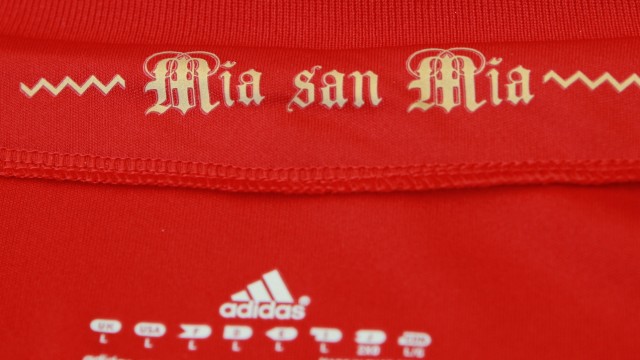
Verzweiflung bei der Suche nach einer Schriftart
ich bin verzweifelt nach der Suche nach einer Schriftart meines eigenen "Vereins".
Es gab leider eine Differenz mit dem ehemaligen Vorsitzenden und der hat das Geheimnis um die Schriftart bis jetzt nicht gelüftet und wird dies auch wohl auch niemals tun.
Deswegen bitte ich Euch mir zu helfen, damit auch in Zukunft nicht alle Plakate, Flyer, Pullis und Briefköpfe eine neue Schriftart benötigen.
Leider habe ich nicht mehr als diese 2 Bilder auf denen die Schriftart abgebildet ist.
Ich kann Dir jetzt zwar den Namen der Schrift nicht aus dem Ärmel schütteln (unsere Frakturexperten wissen da sicherlich mehr), aber ich würde Dir gerne spontan empfehlen, einen sauberen Schnitt zu machen und Deinem Faschingsverein ein neues visuelles Erscheinungsbild zu spendieren.
Ich vermute mal, dass es Euch ursprünglich darum ging, über diese Schriftwahl das Thema Tradition auszudrücken, denn Faschings- und Karnevalvereine haben ja häufig eine ganz beachtliche, aber ich bin mir ganz sicher, dass sich das auf andere Weise besser transportieren ließe. Nun weiß ich natürlich nicht, ob ein solcher Wechsel für Dich/Euch überhaupt in Frage käme und will Dir da auch nicht zu nahe treten (gerade weil Fasching vor der Tür steht und Du jetzt vermutlich andere Sorgen hast, als über das visuelle Erscheinungsbild des Vereins nachzudenken). Aber vielleicht wäre es ja eine Möglichkeit, dass Du Dir nach dem Aschermittwoch dazu noch mal in aller Ruhe Gedanken machst? Du würdest hier im Forum sicherlich auf hilfsbereiten Rat stoßen, wenn Du mit einem solchen Vorhaben anklopfst.  :-D
Mir fallen spontan "English Gothic" als Stichworte ein, irgendwas in der Richtung:
@Kathrinvdm: Danke für deinen Tipp, aber leider ist dies nur bedingt möglich, weil das Logo, also auch diverse Utensilien, darauf aufgebaut sind! ;)
Jovaregg, pfeilgrad.
Bin aber auch Nicht-Fußballer, obwohl aus München, daher kannte ich das noch gar nicht …
Irgendwie habe ich allerdings das Gefühl, dass diese Anglo Text nicht das original ist. Habe sie mir mal heruntergeladen, und sie schaut einfach zu sehr nach Autotrace-Hauruck-Digitalisierung aus.